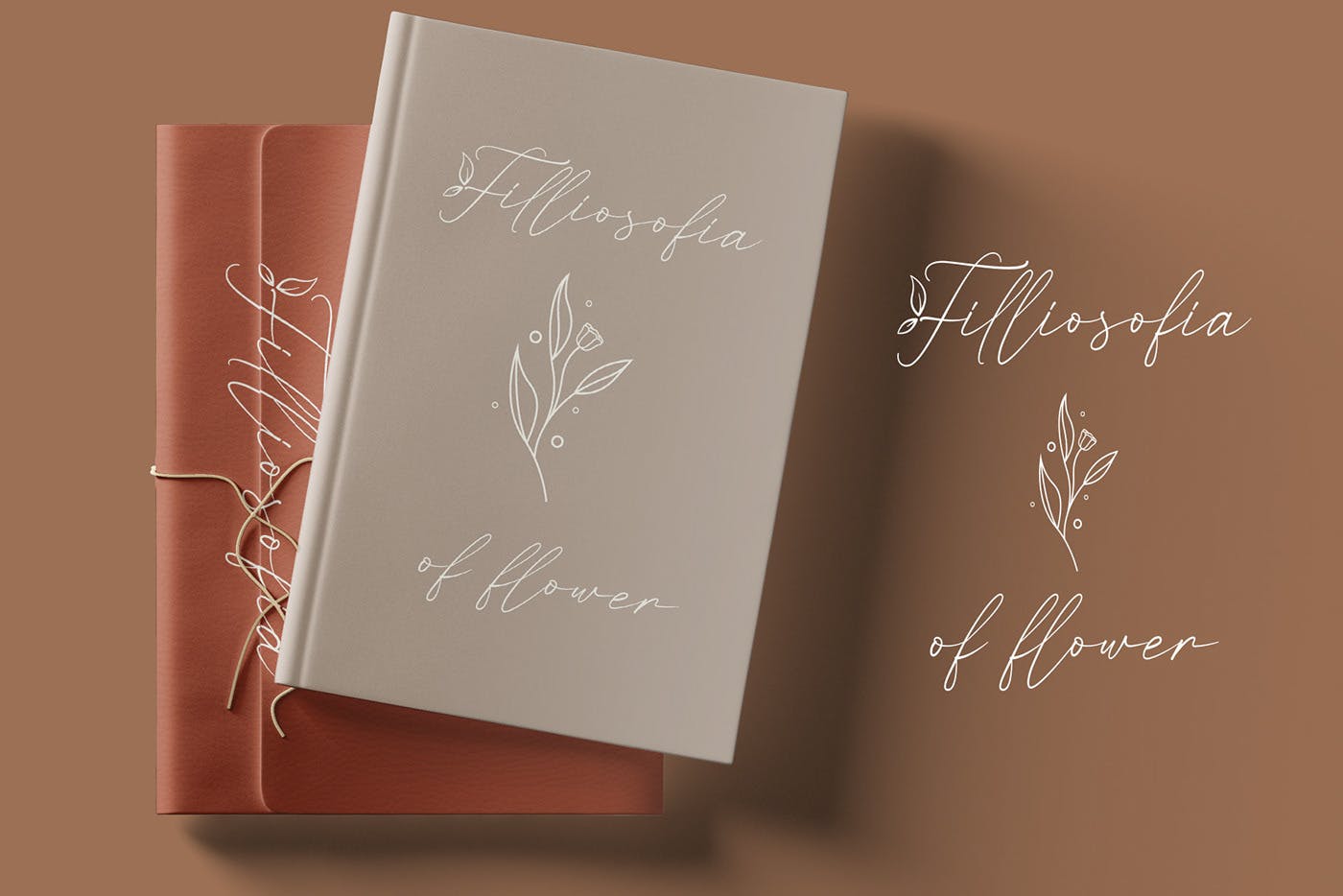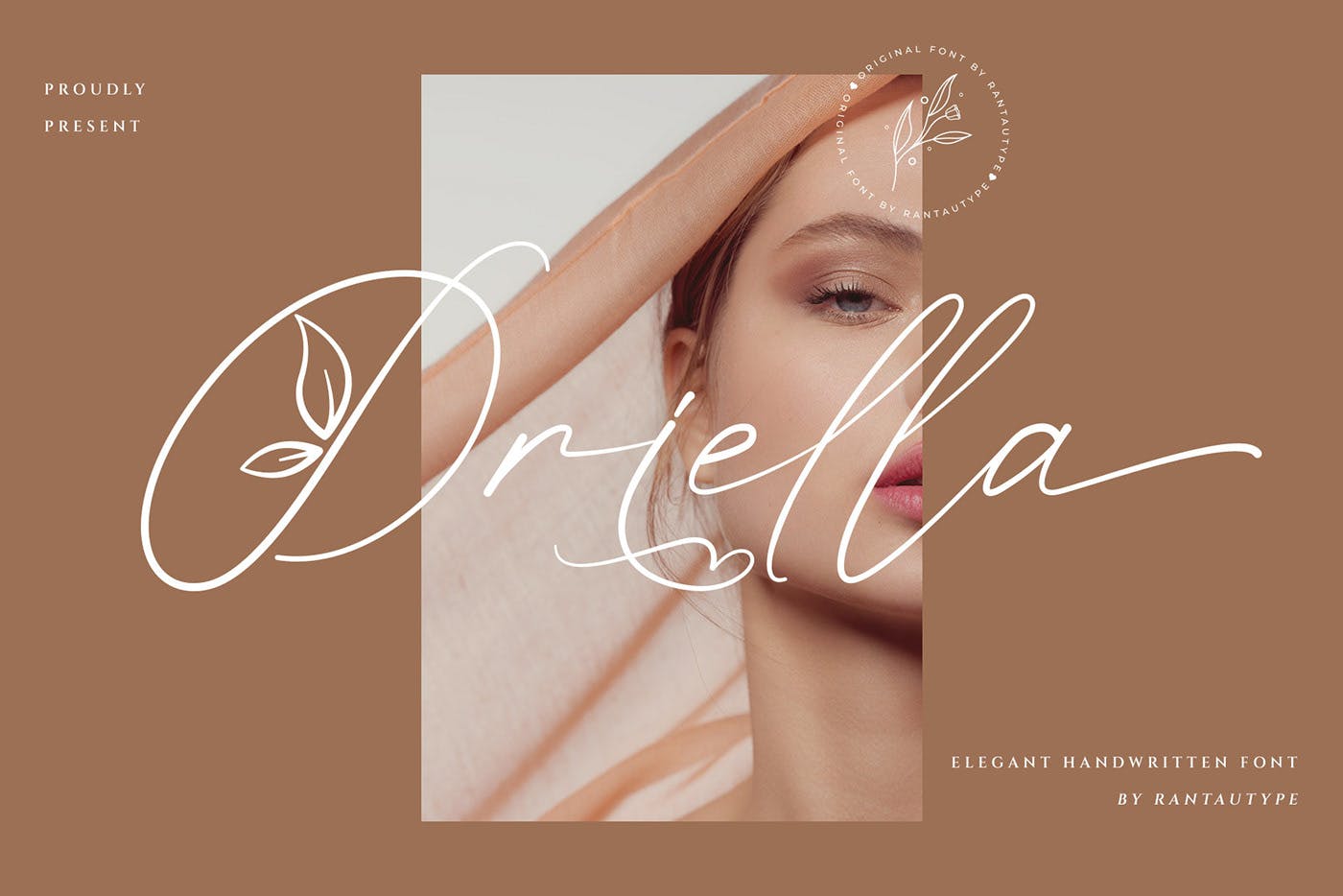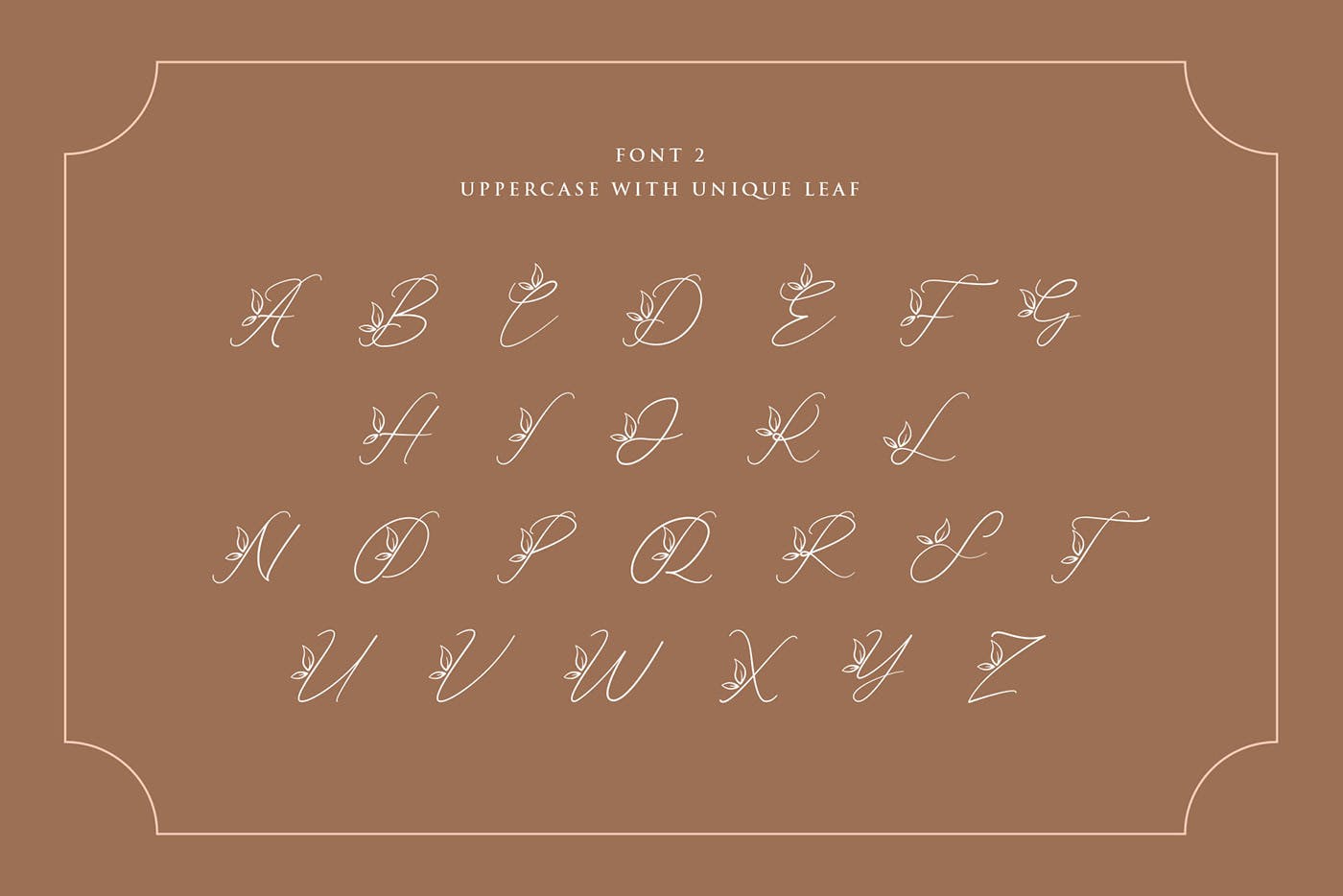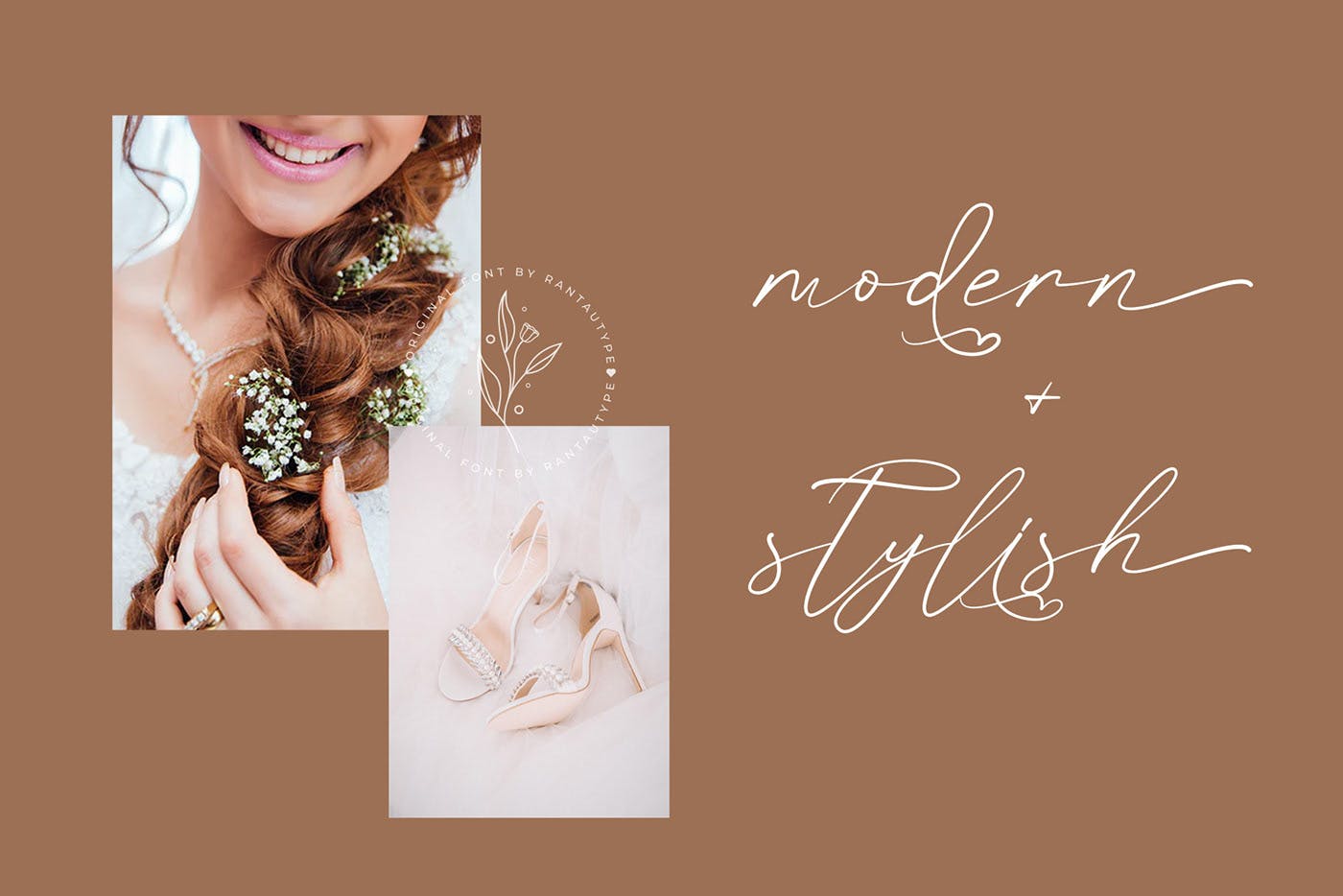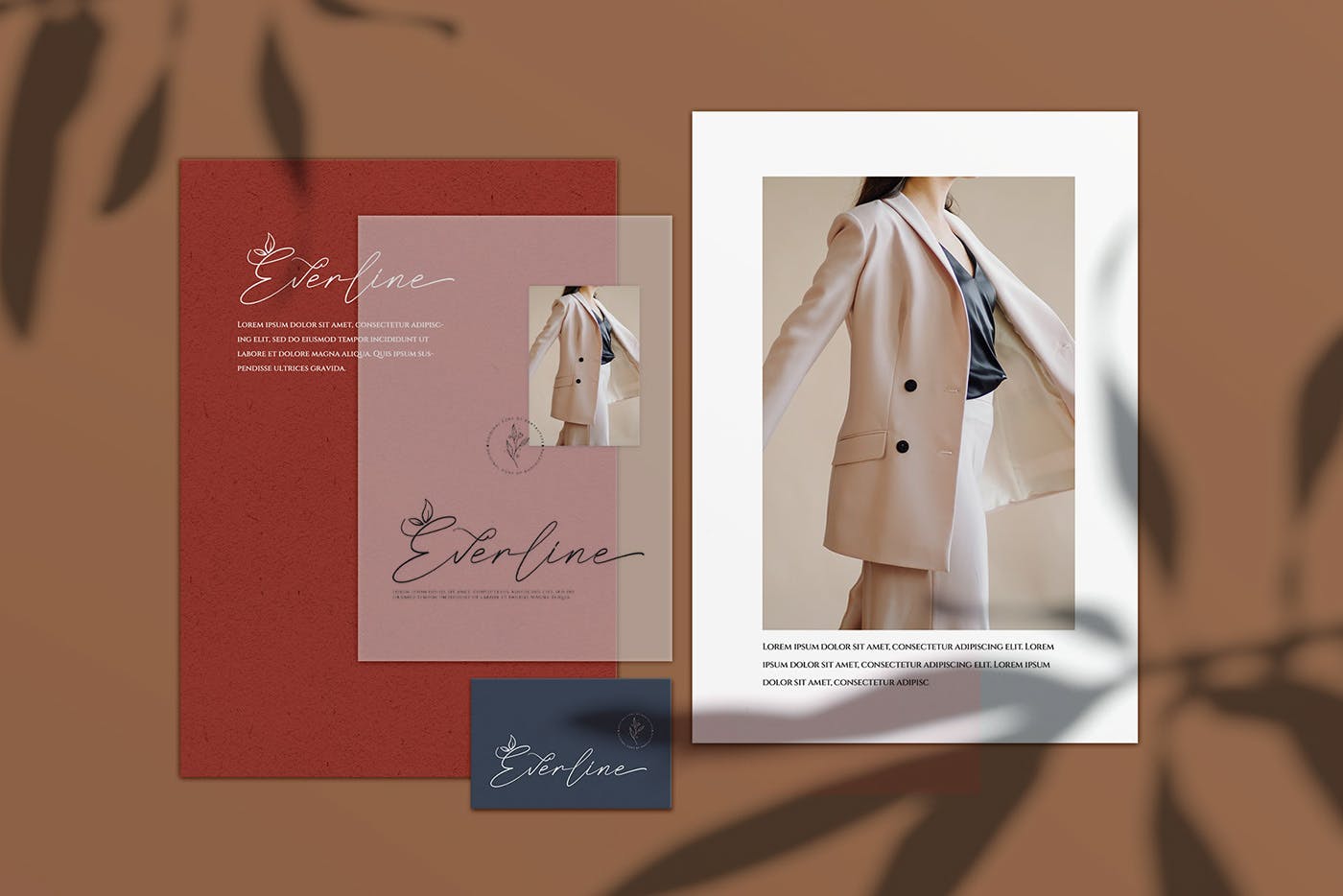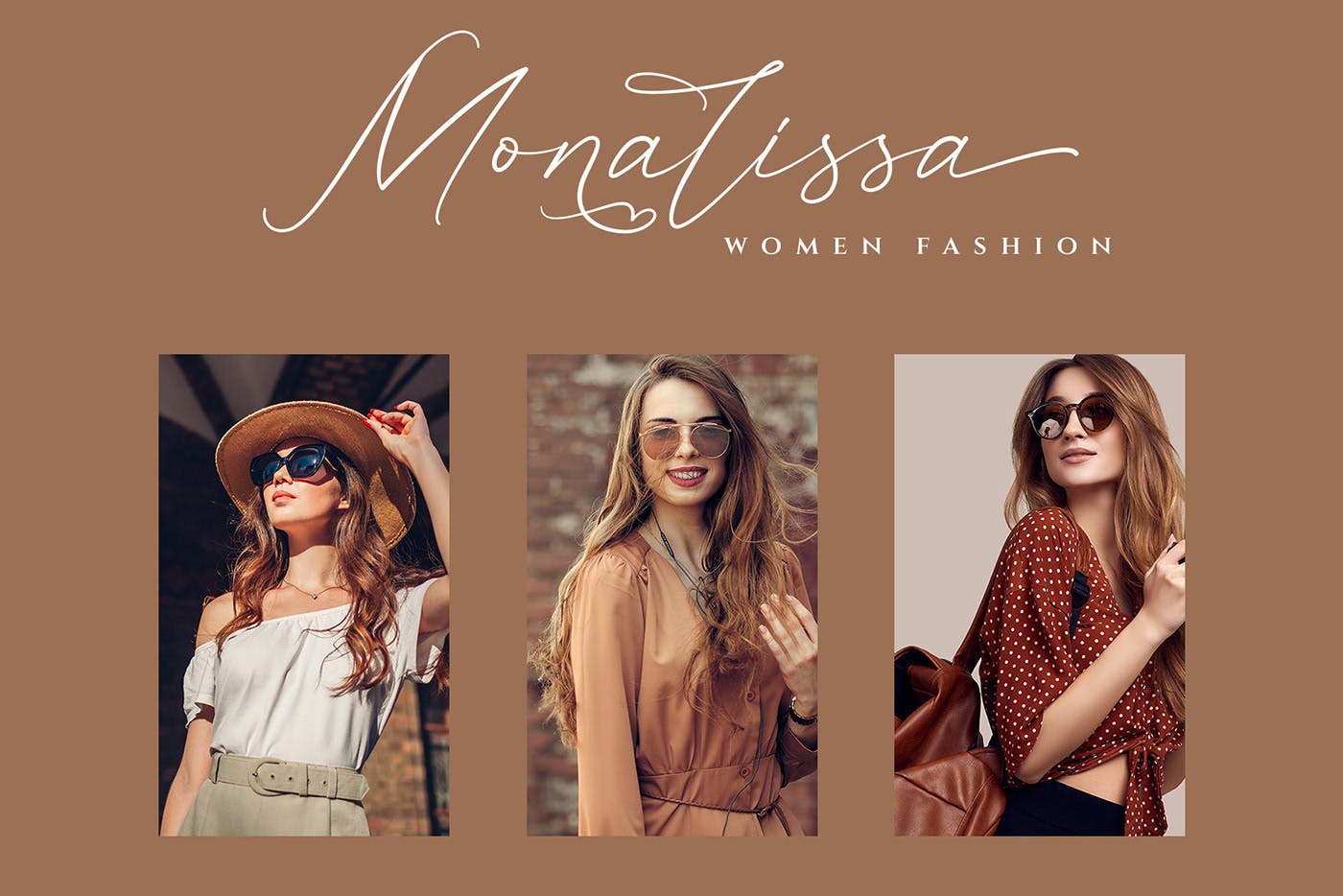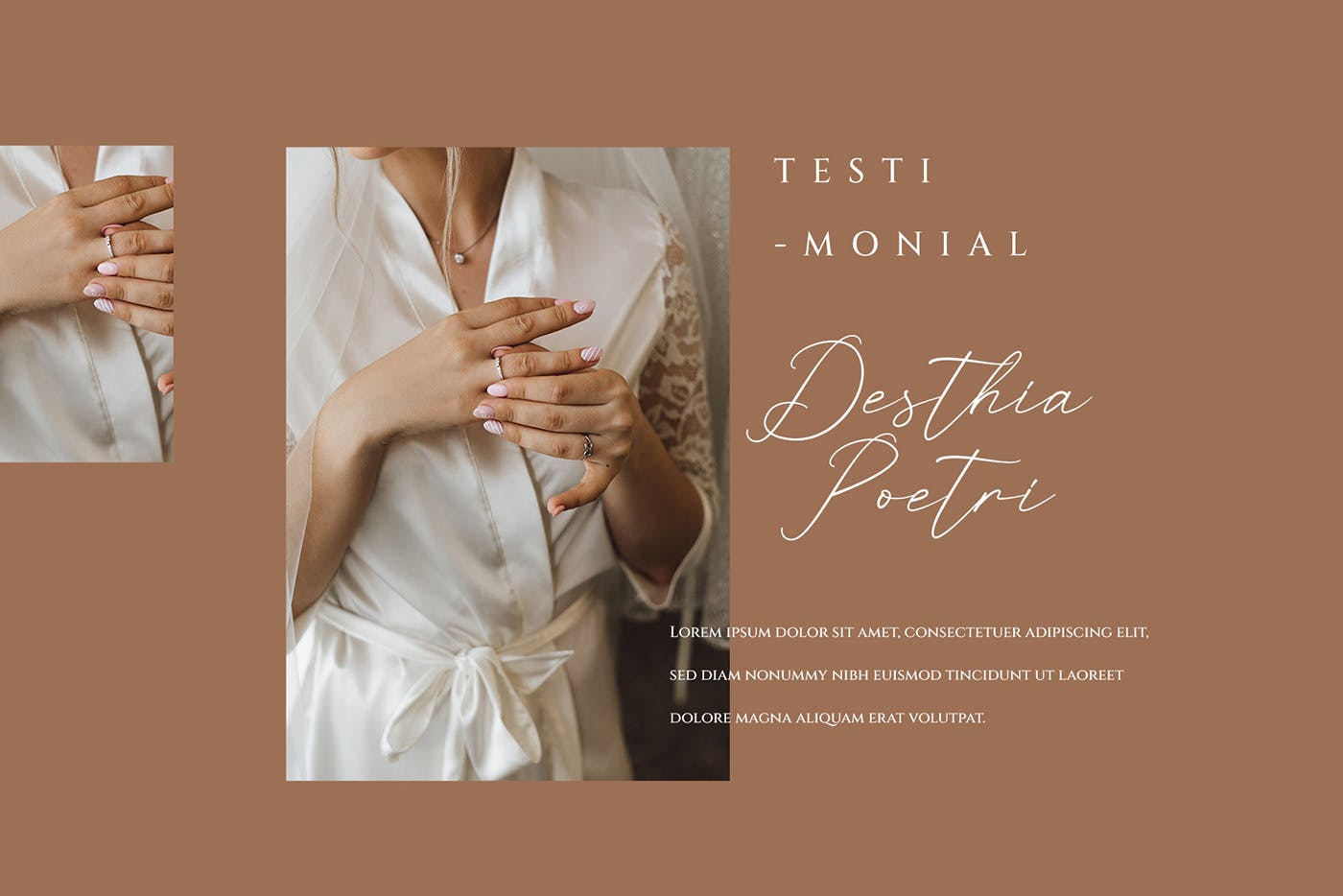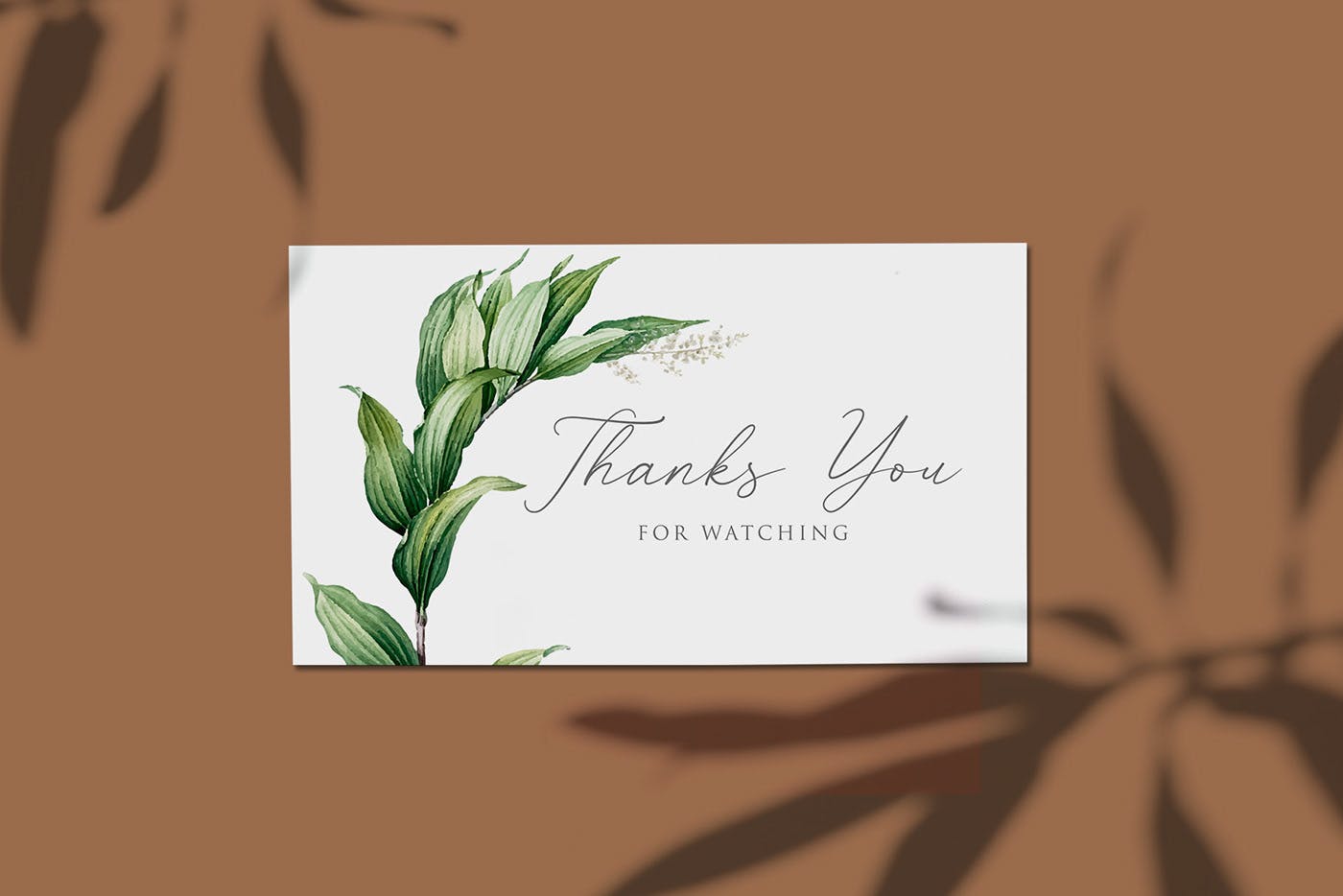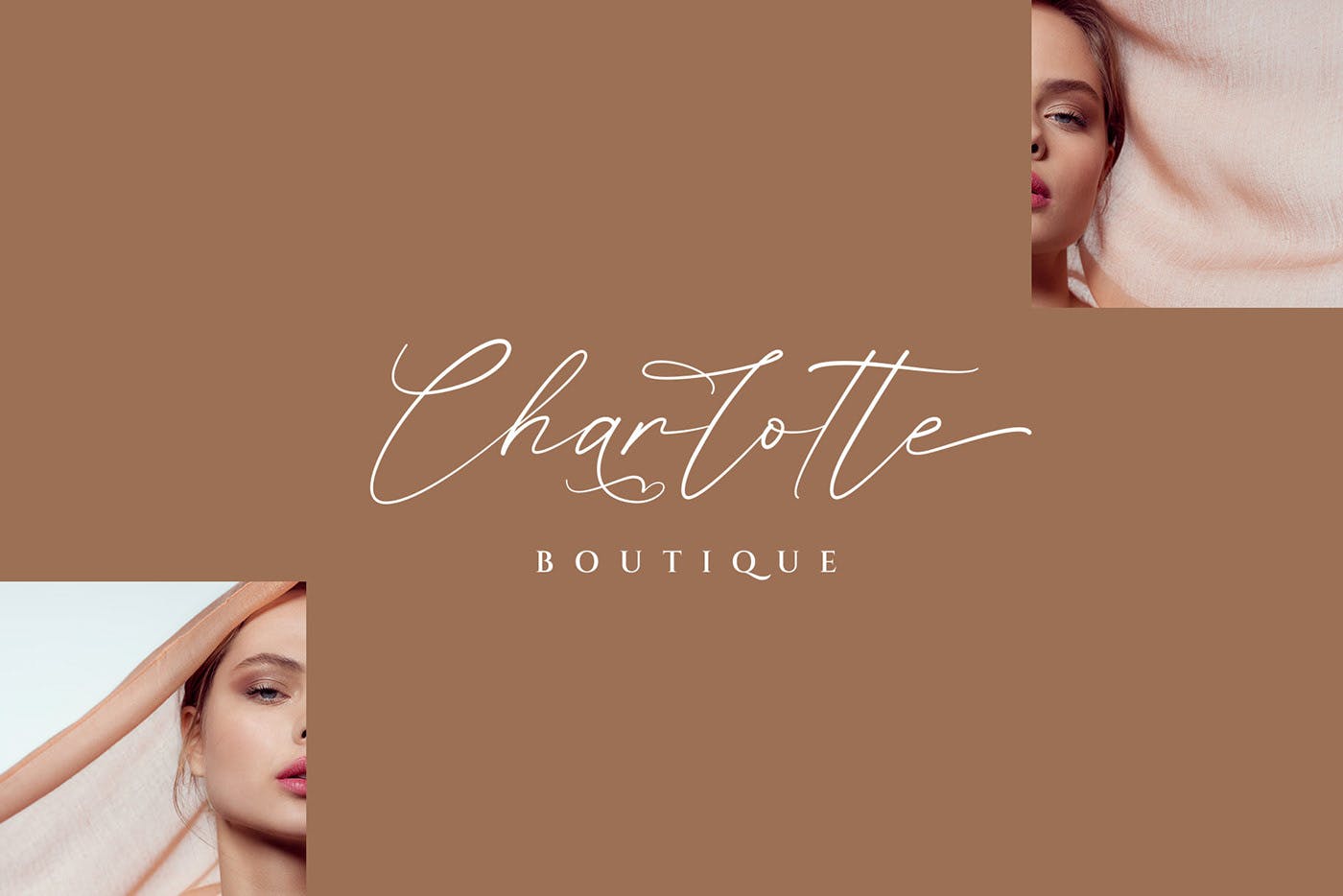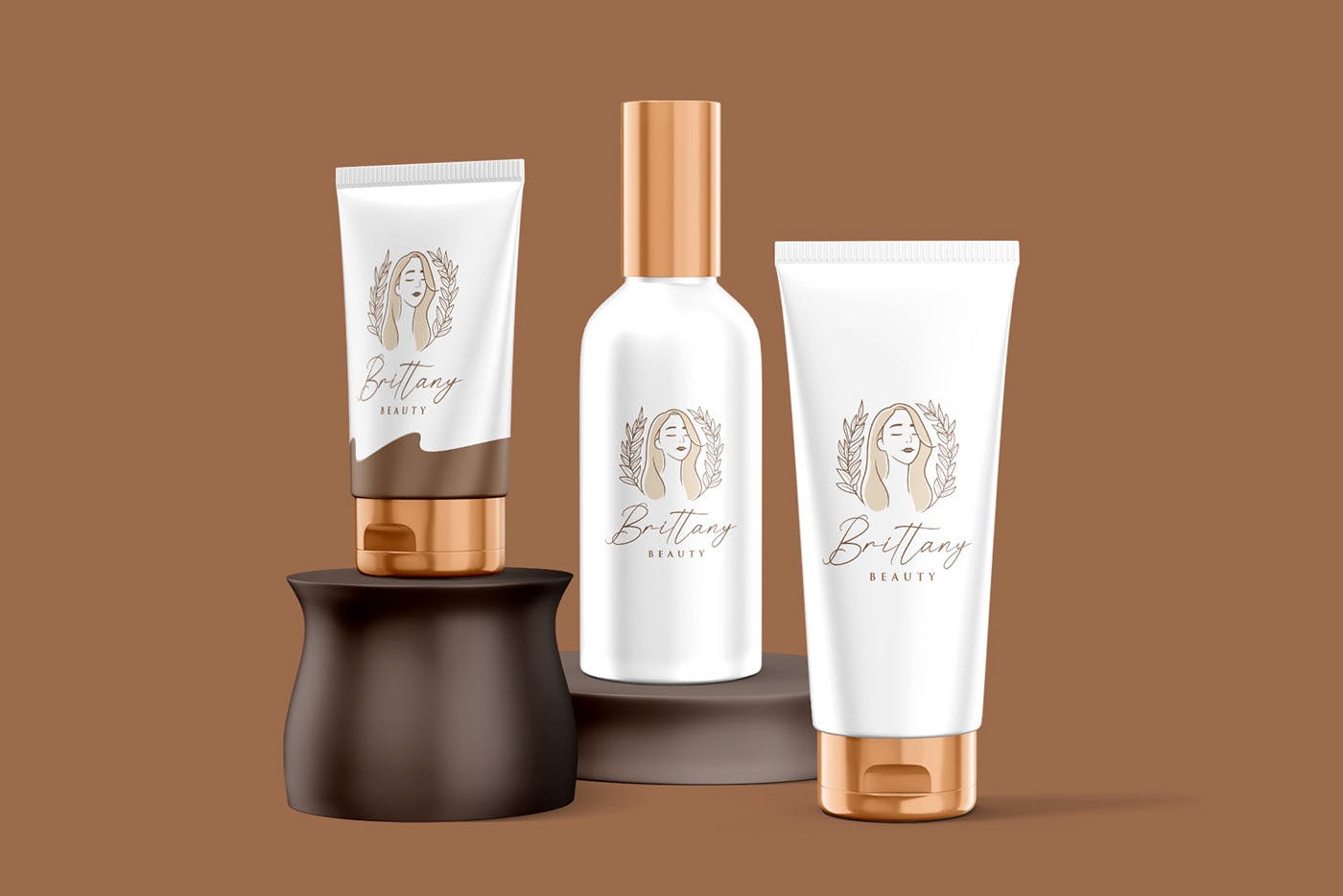
سلام خانمها و آقایان! با افتخار فونت دستنویس لوکس دیگری به نام “Oriella” را معرفی میکنیم. این فونت با سبک زیبا و حرفهای خود، ظاهری شیک، لوکس، مدرن و خوانا دارد. Oriella به راحتی قابل استفاده است و طراحیهای شما را زیباتر میکند. همچنین شامل دو نوع فونت با حالت عادی و حالت بزرگنویسی با برگ است که به شما کمک میکند تا طراحیهای خود را خاصتر کنید. این فونت انتخابی عالی برای واترمارک در عکاسی، امضا یا طراحی لوگوی امضا، نقلقولها، جلد آلبوم، مجلات، کارت ویزیت و بسیاری پروژههای طراحی دیگر است. Oriella اینجاست تا کار شما را به سطح بالاتری برساند!
ویژگیها: